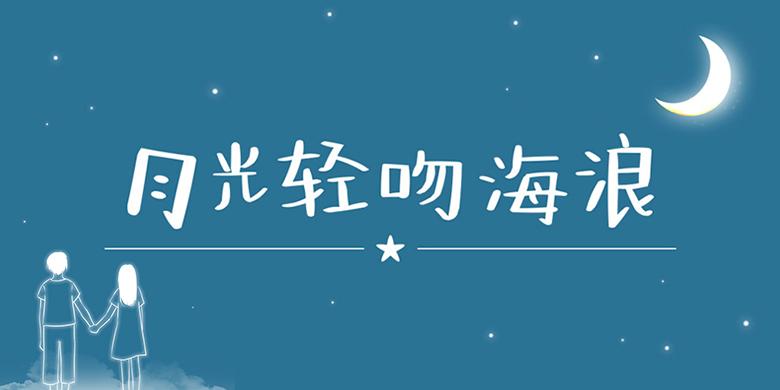
方正手迹-月光轻吻海浪
品牌:方正手迹设计师:刘晔发行时间:2019字库编码:大陆简体(GB2312-80)分类:创意书写字体属性:精品字
方正手迹-月光轻吻海浪
整体横细竖粗,结构呈正方形。书写严谨,充满活力,意趣十足。整体风格新颖可爱,特色鲜明。适用于少年儿童类的书刊、品牌广告和产品包装设计,以及社交网络的个性化用字。